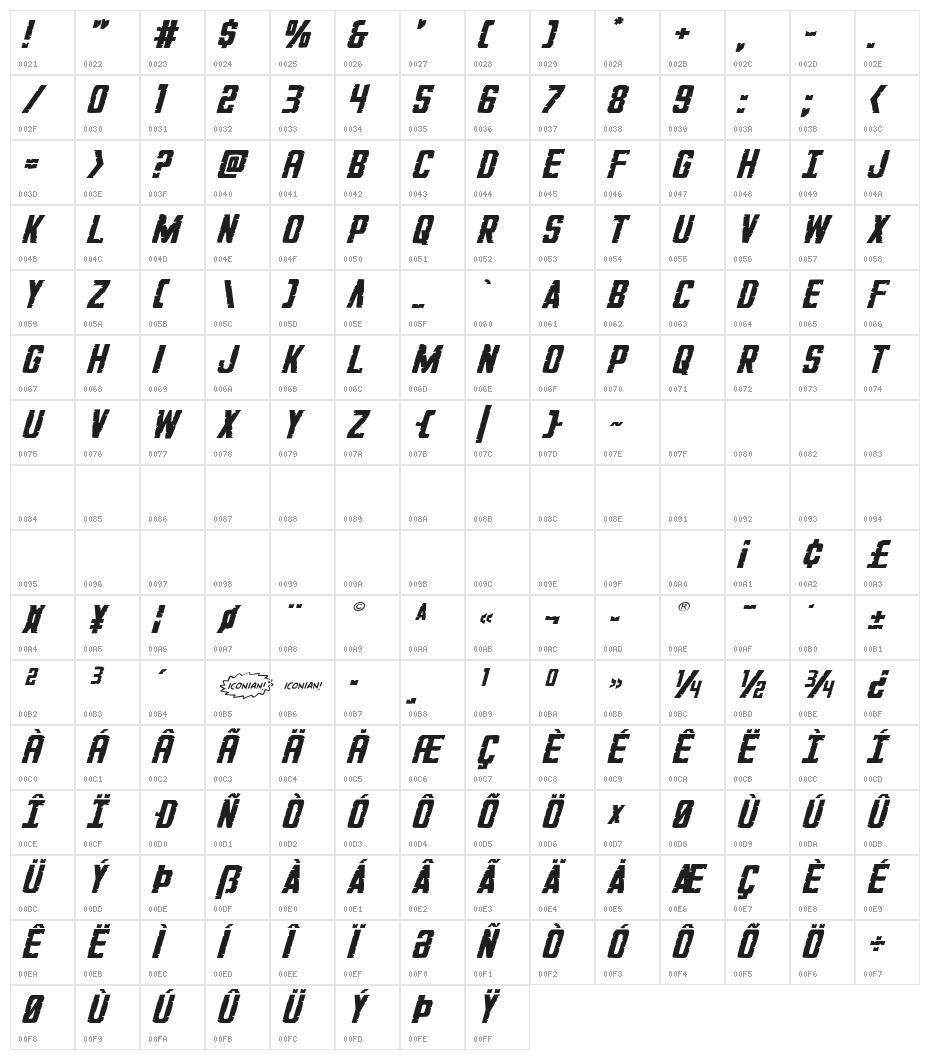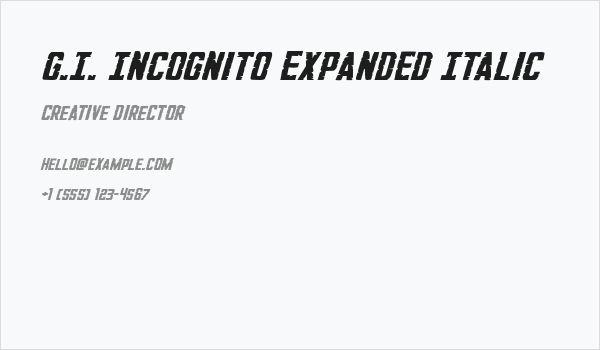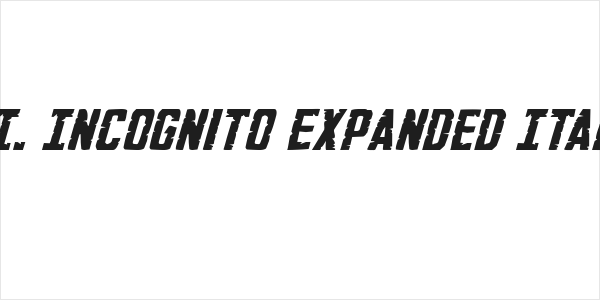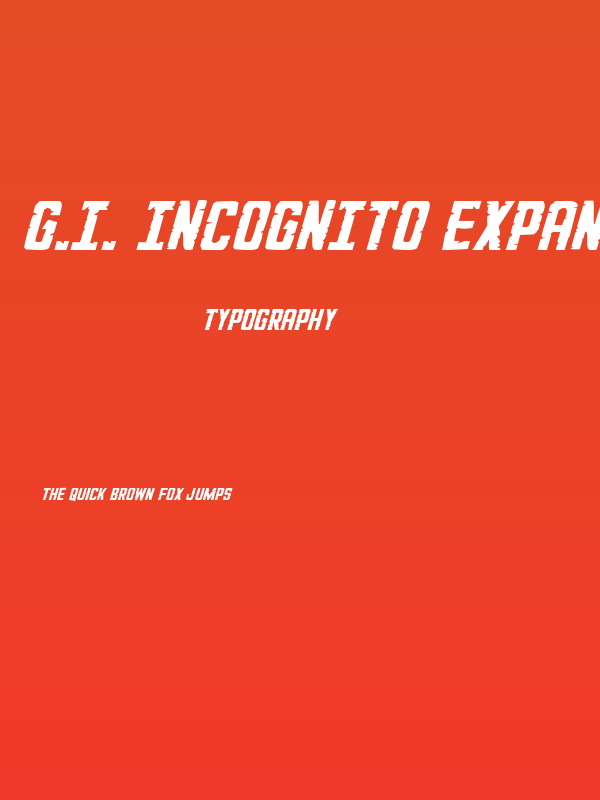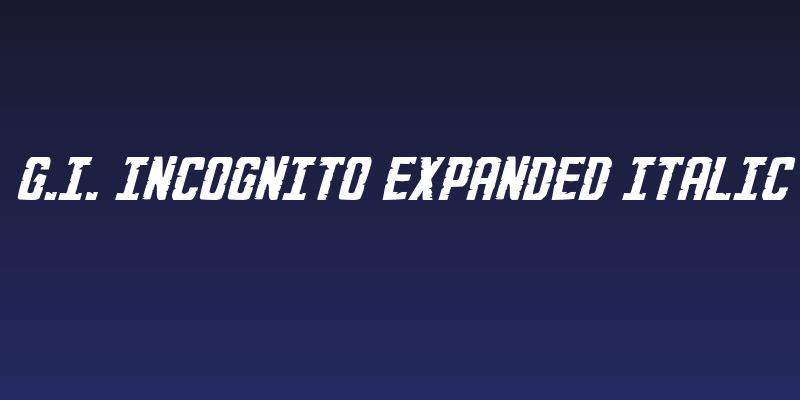
G.I. Incognito Expanded Italic Font
✎ Distorted Eroded
| Nome | G.I. Incognito Expanded Italic |
| Peso | Expanded Italic |
| Categorie | Distorted Eroded |
| Larghezza | Expanded |
| Stile generale | Dynamic and Edgy |
| Progetti proposti | Ideal for sports branding, action movie posters, dynamic advertising campaigns, and any project needing a bold, impactful statement. |